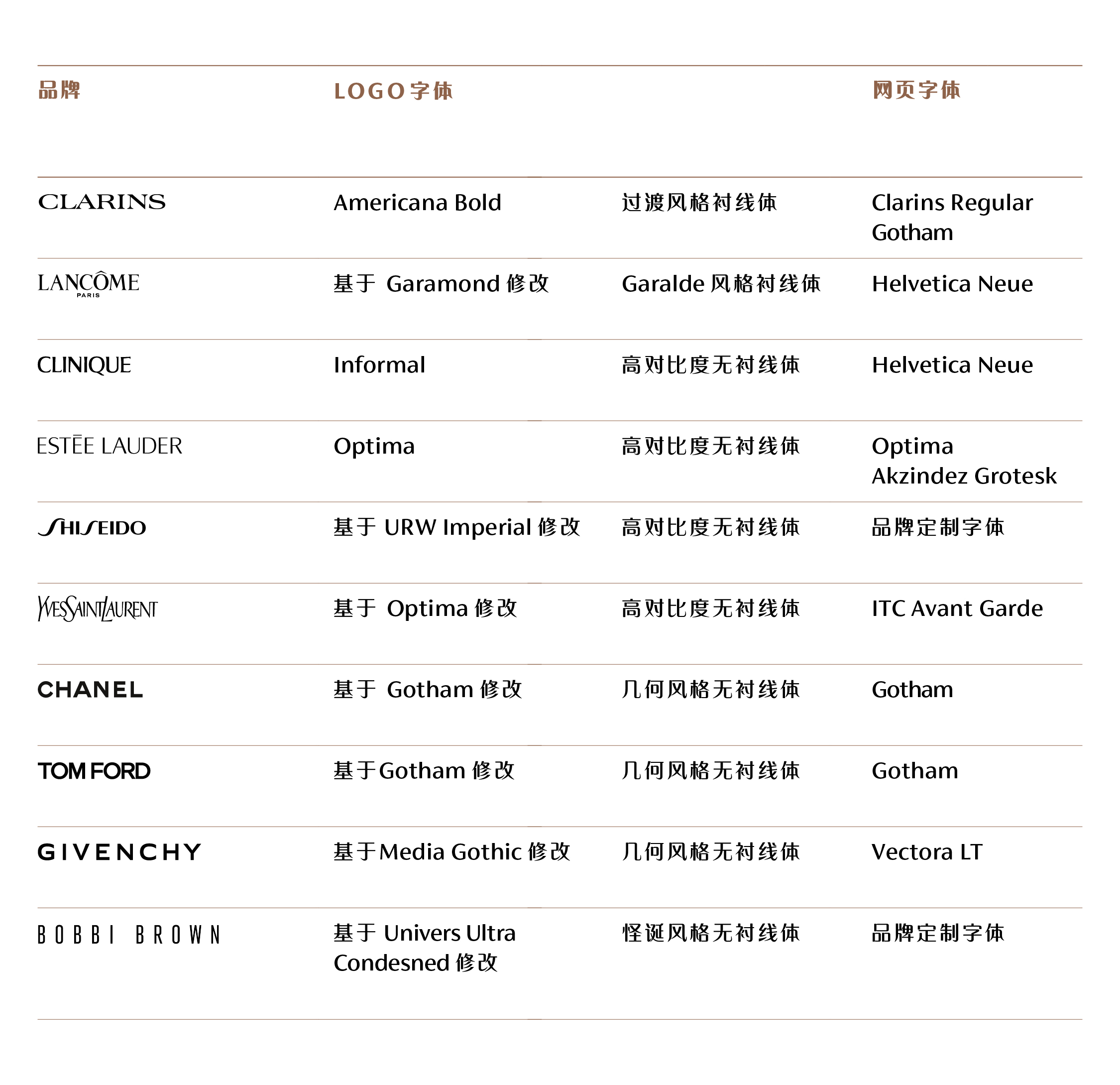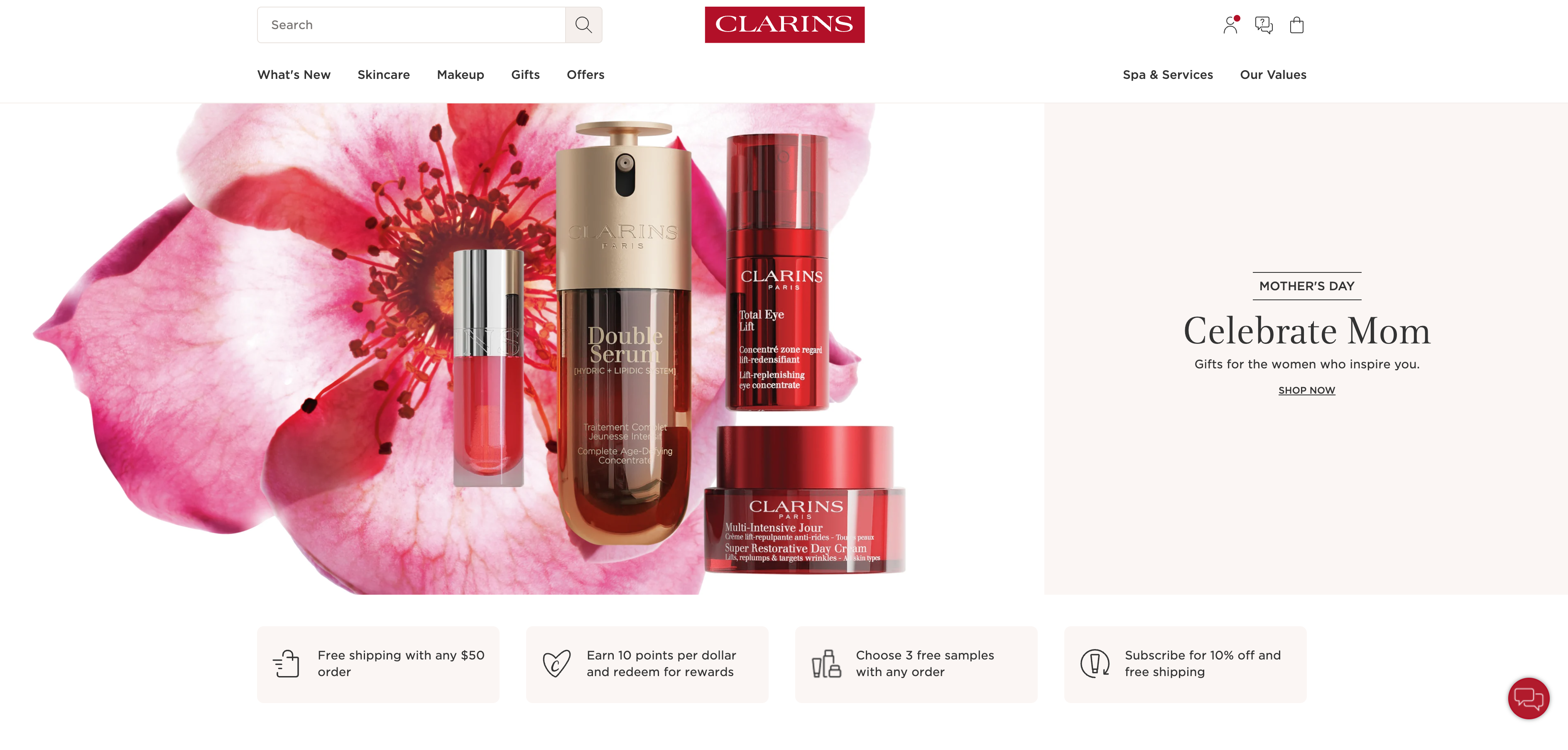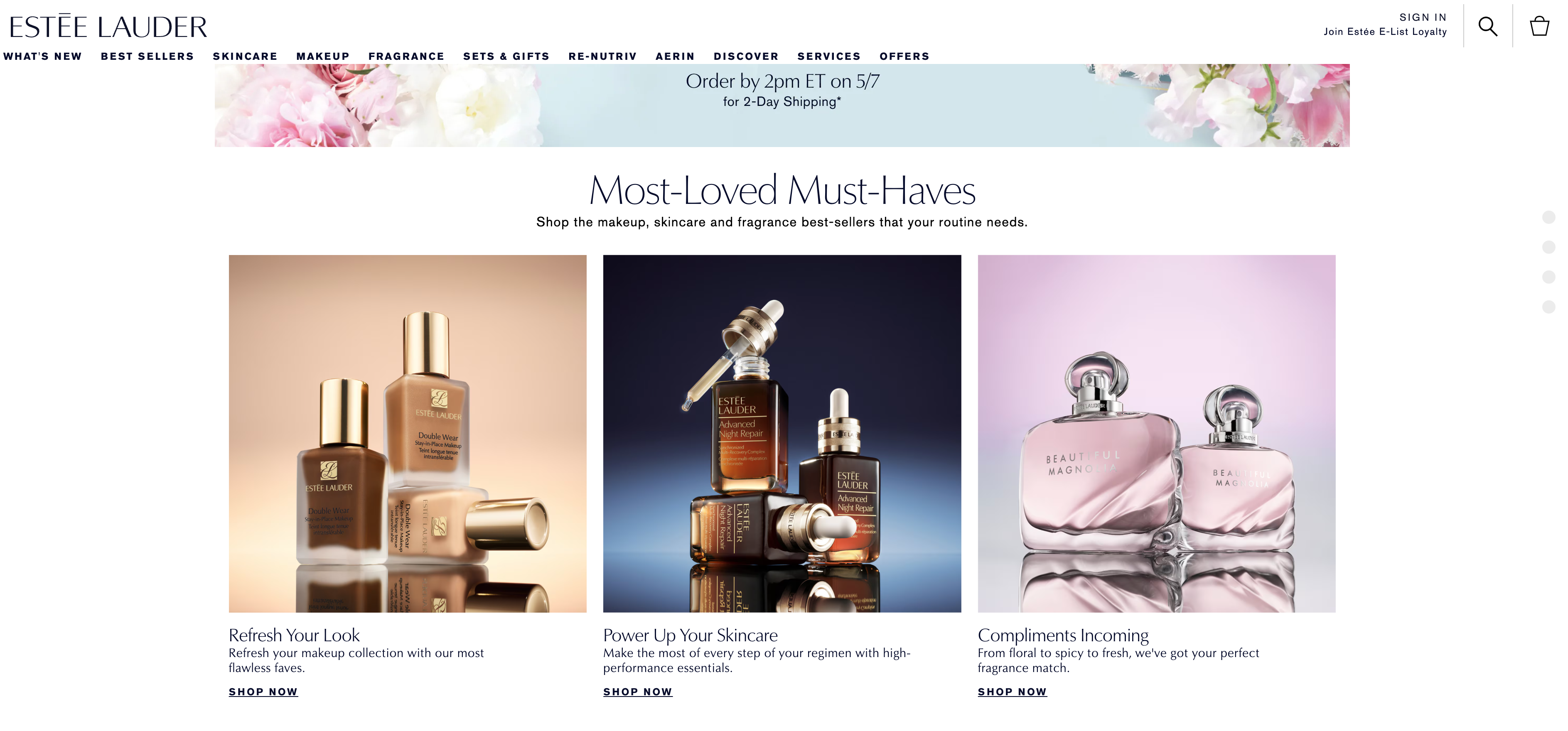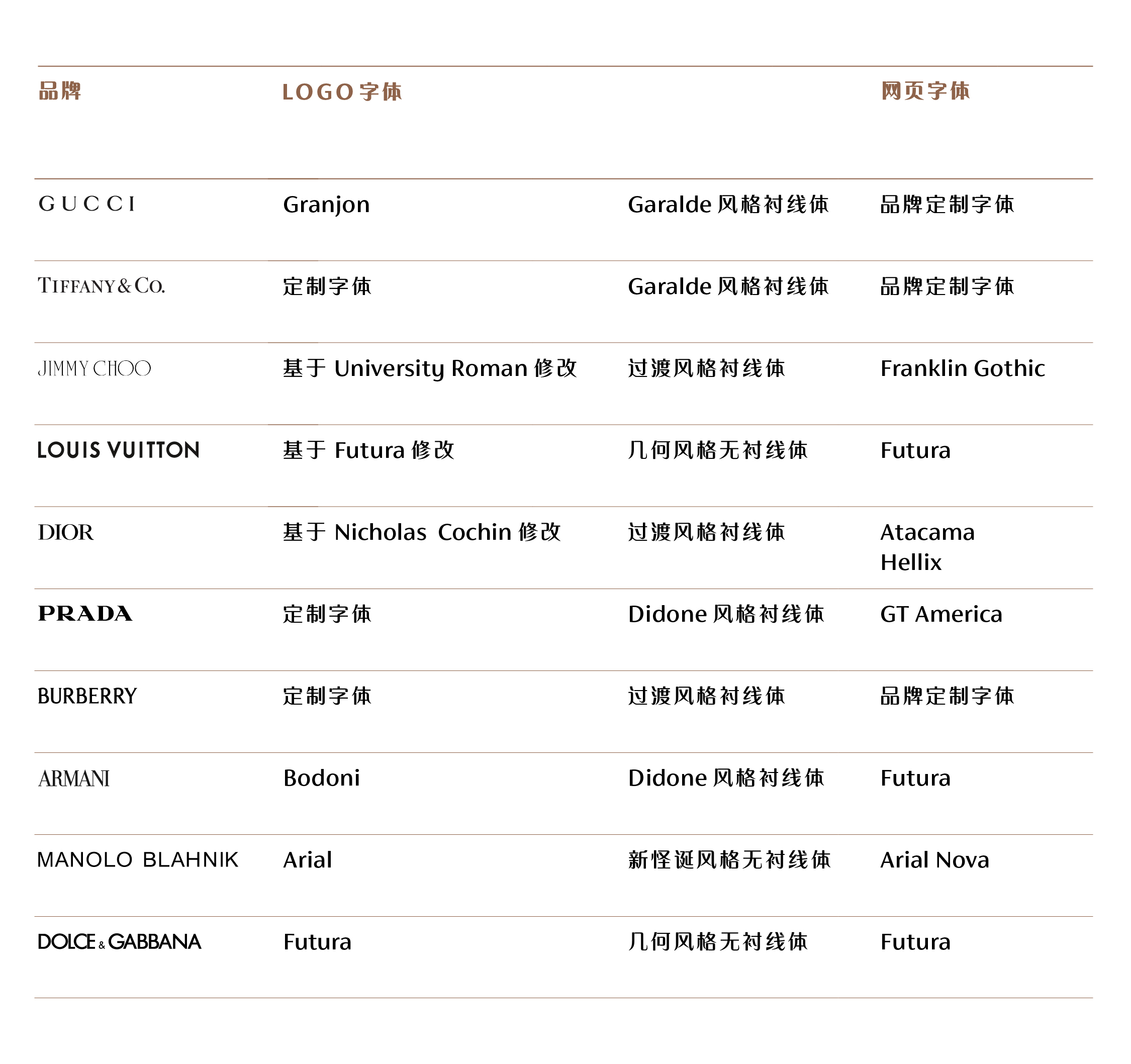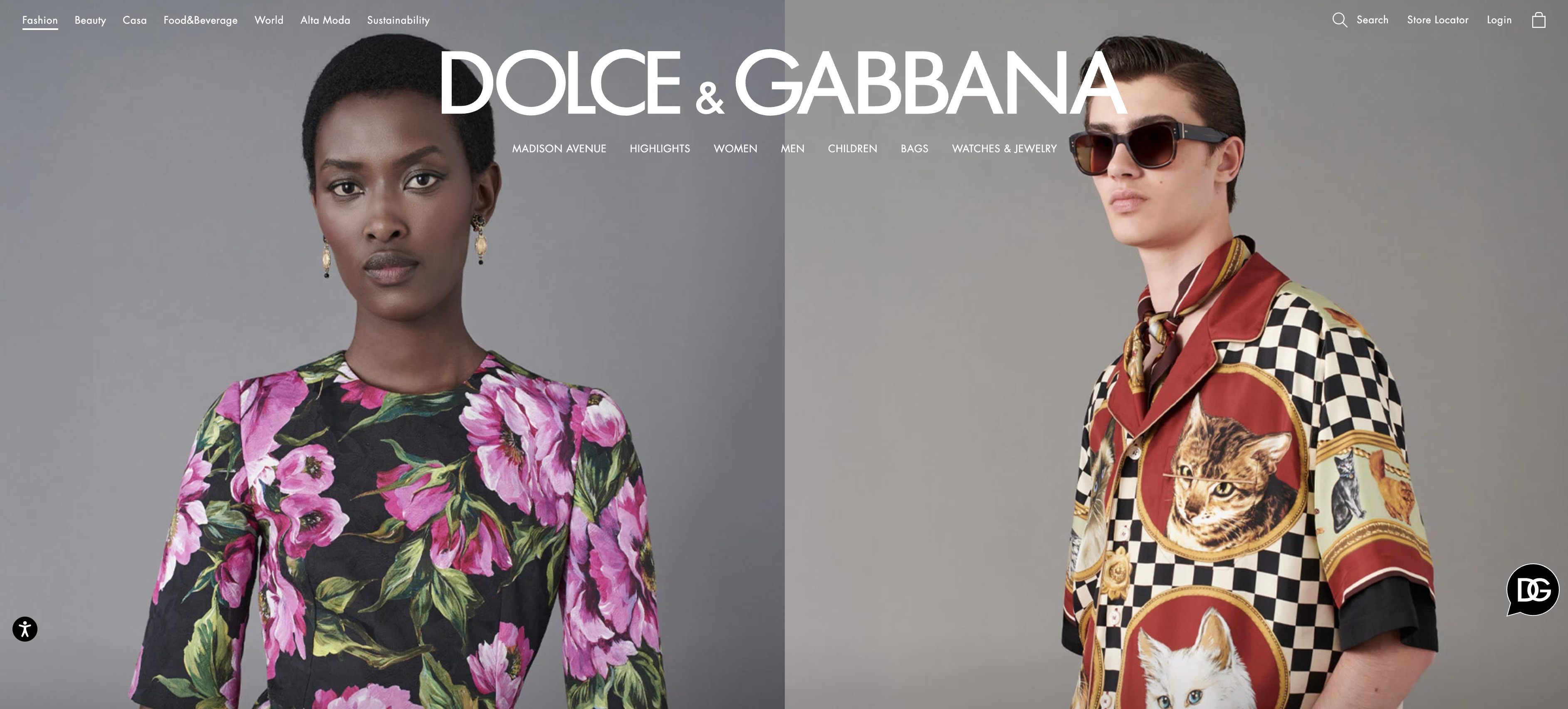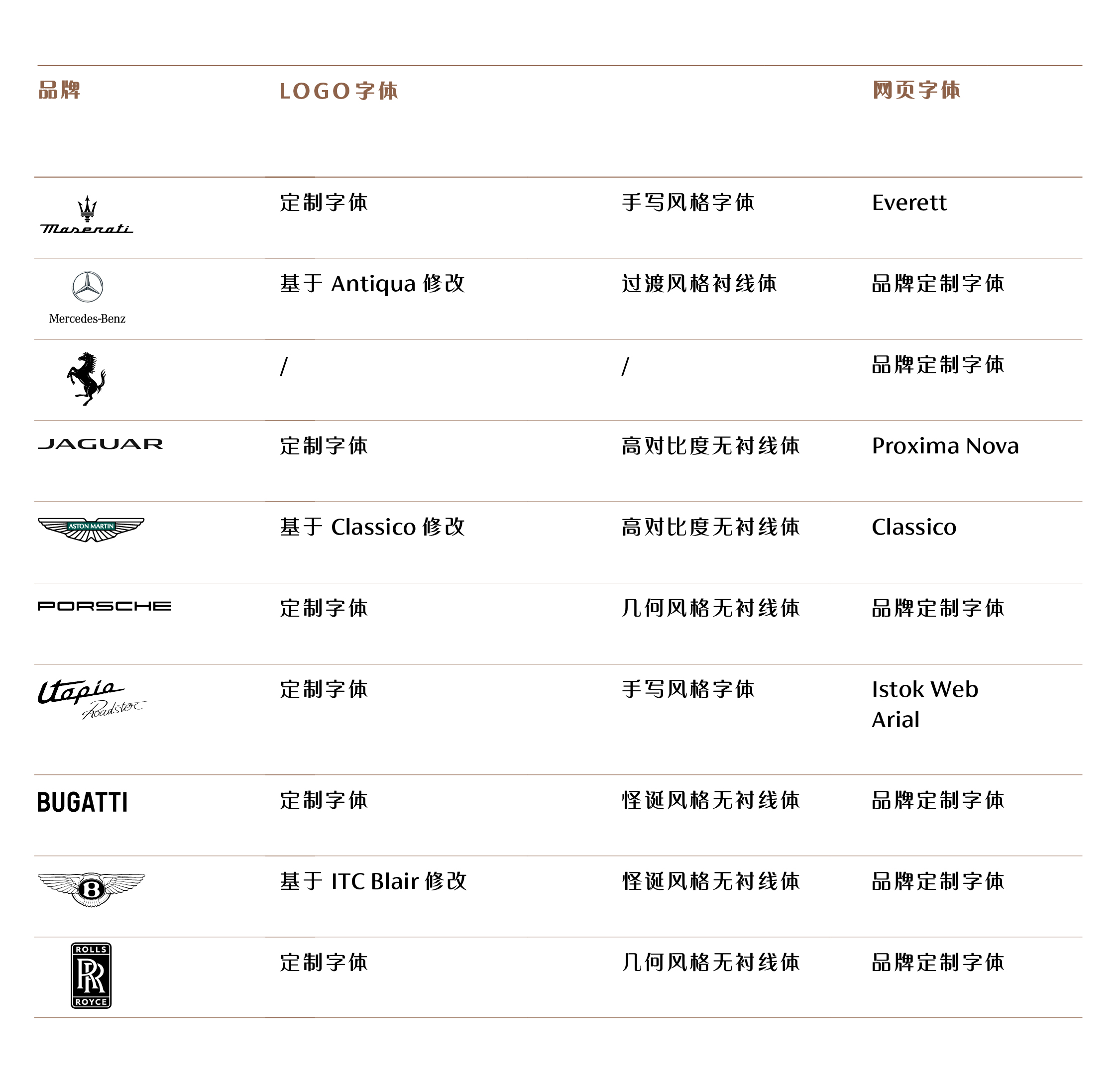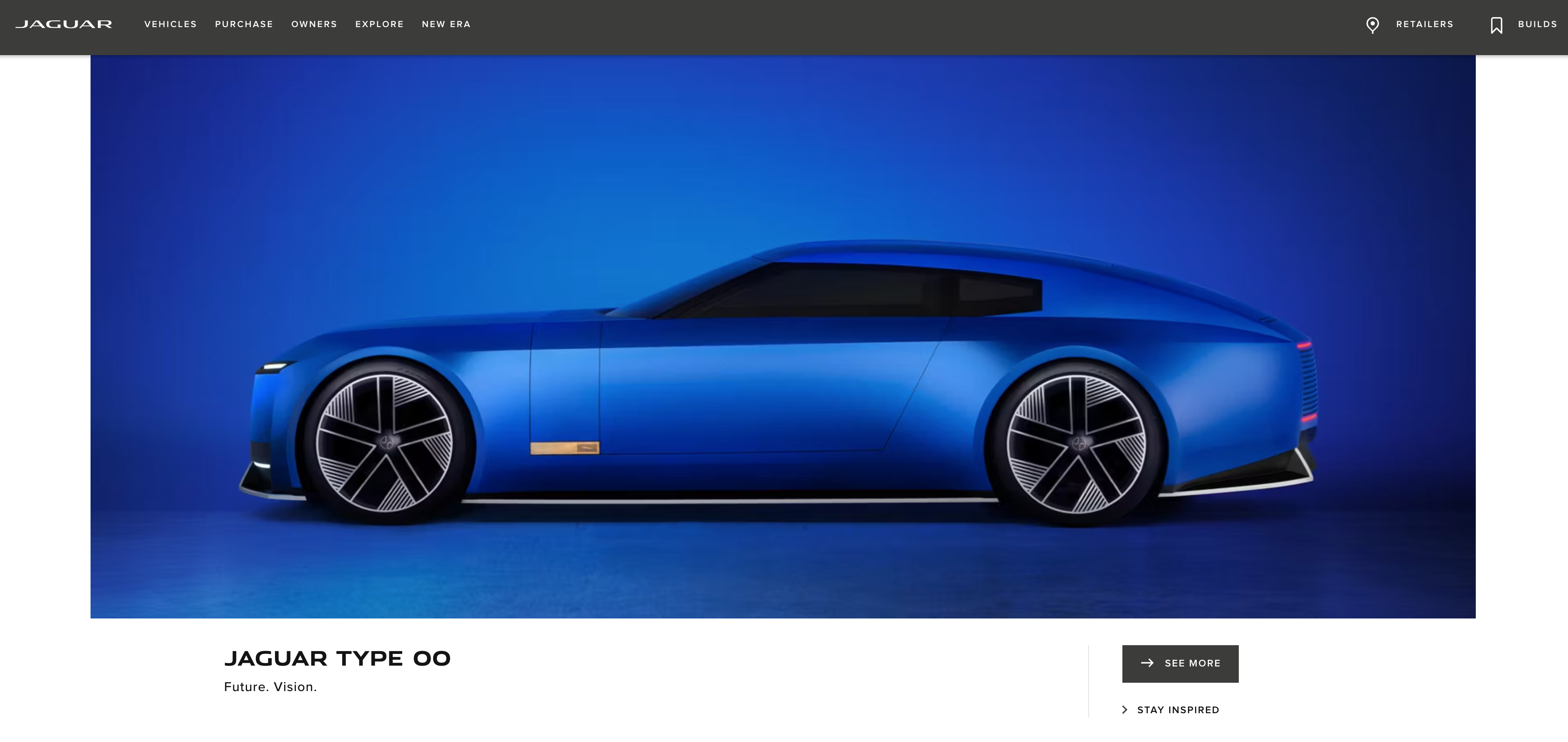
为什么一看就很贵?奢侈品牌在用这些字体策略……
导读:
提起「奢华感」,你会想到什么?是柔光下闪耀的 LOGO,还是印在包装上的那一抹优雅衬线?在数字化叙事的今天,奢侈品牌早已不再只靠金属印刷和高定剪裁取胜,屏幕上的每一个字体选择,都在无声中传递品牌的品位与态度。
本文聚焦美妆、时尚与汽车三大行业,剖析 30 个高奢品牌如何通过字体构建独特的视觉语言:全大写、衬线体、粗细对比明显的笔画……它们是否就意味着「奢华」?
如果你正在寻找打造高级感的灵感,或想让品牌在视觉上脱颖而出,这份关于字体的观察与分析,值得参考。
在数字时代,奢华早已不再遥不可及,你无需成为富豪,也能在社交媒体尽览顶级品牌的风采。正如广告公司 BETC 主席兼创始人 Rémi Babinet 所言:「奢侈的定义正在演变,它不再只是价格与稀有的代名词,更是一种能与时代对话的文化象征。」
在视觉传达上,字体正是连接传统与当下的关键,需要找到微妙的平衡:既承载底蕴,也要具备冲击力与时代感。
* 高对比度(High Contrast Sans Serif)指笔画粗细对比明显,本文其余部分亦同。
1.1 刚柔并济的字体美学
反直觉的是,美妆品牌并不都偏好纤细衬线体、柔和配色和华丽模特,反而常用黑白配色、大胆视觉和全大写字母,不仅 LOGO 和导航如此,甚至正文也不例外。
通过全大写字母和黑白极简配色,Tom Ford 在数字端传达出一股坚实自信的气场。
全大写虽在可读性上略有牺牲,但视觉风格更鲜明。Tom Ford 的官网完全不用小写字母,展现出强势、张扬又现代的气场。
有趣的是,几乎所有品牌 LOGO 都采用了全大写,其中超过一半使用笔画粗细对比明显的字体(如 Optima),40% 选择粗重无衬线体。网站主字体方面,七成偏好几何无衬线体,40% 使用高对比笔画设计,呈现出多样又鲜明的风格取向。
1.2 以行业通用字体构建「高级感」
香奈儿的 LOGO 使用了几何无衬线体 Gotham,凝练了品牌的优雅格调。网站也一以贯之,统一使用粗体全大写 Gotham,确保品牌调性。
这些品牌在字体选择上呈现出高度一致性,Gotham 和粗细对比明显的无衬线体 Optima 是最常见的选择。例如香奈儿标志性的全大写几何风格粗体,优雅而高贵,与品牌形象如出一辙。
娇韵诗选用了一款现代感的衬线体,风格接近 Baskerville,优雅得体,非常适合展现美妆产品的质感。
在强调差异化、却易被模仿的市场中,这种字体上的趋同颇为耐人寻味。对于初创品牌而言,通用字体也能帮助迅速复制出类似的高级感。
1.3 衬线体 VS 无衬线体
美妆行业的字体大致分为两类:一类借助衬线和粗细明显的笔画营造传承感,另一类则偏好几何或更张扬的字体,追求现代与个性。后者若搭配得当,同样能展现奢华气质,但更需在视觉上与平价品牌拉开差距。
雅诗兰黛网站融合轻盈纤细的 Optima 字体、大篇幅精致图像,以及品牌标志性的深蓝色,整体氛围正式而不失优雅。
尽管衬线体常被视为更具高端气质,但实际使用并不广泛。娇韵诗与兰蔻凭借现代衬线体打造出独特的经典感,而雅诗兰黛采用的 Optima,也展现出优雅与辨识度。
在竞争激烈的市场中,脱颖而出并非易事。相比其他行业,美妆品牌更倾向于选择不那么普遍泛用的字体,以增强辨识度和品牌印象,区别于竞争对手。
2.1 极简之中见锋芒
多数时尚品牌以大胆摄影搭配简约字体,风格与美妆行业相近:留白充足、色彩强烈,偏好几何风格或笔画粗细明显的字体。
杜嘉班纳的 LOGO 及网页主字体都选用了 Futura,以几何理性的结构传达出现代感与坚定气质。
在网页主要字体的选择上,几何无衬线体尤为流行,占我们调研品牌的 80%,最常见的是 Futura(美妆品牌们则更偏好 Gotham),也有部分品牌在近几年启用了自己的定制字体。
2.2 衬线体与全大写
70% 的品牌 LOGO 采用了衬线体,传递出经典感,但纤细笔画在屏幕、尤其小尺寸下易失真。这些字体多为印刷时代设计,难以适应数字环境,因此一些品牌即便视觉设计出众,网页内容仍使用系统默认字体。
迪奥官网以衬线体为主,无衬线体为辅且全大写排版,构建起优雅纤细的视觉观感。
和美妆、汽车行业类似,全大写也非常常见。调研的十个品牌中,有九个在导航菜单和 LOGO 中采用了全大写,唯一例外是 Dior。
2.3 在移动端占据用户心智
品牌识别至关重要,而字体正是其中最容易被忽视、却极具辨识度的要素之一。虽然并非每个品牌都深入了解字体细节,但在构建品牌价值、传递调性时,它所起的作用不容小觑。
尤其在移动端这个展示空间有限、用户注意力高度分散的主战场中,一款精心挑选且与品牌高度契合的字体,往往能在第一时间传达出品牌的格调与专业性,成为区别于其他品牌的关键视觉符号。
3.1 力量背后的优雅设计
汽车行业仍被普遍视为男性主导的领域,因此,观察它是否与传统上面向女性的美妆和时尚行业在字体使用上存在相似之处,颇具趣味。
在字体选择上,车企需权衡诸多要素:如何在传达力量、速度与精准的同时,也体现奢华感?
3.2 LOGO 的多样性
在 LOGO 字体上,汽车品牌呈现出丰富多样的风格,从旧式、板状衬线体,到几何、怪诞、人文主义无衬线体皆有覆盖。
奢华感的表达也分为两类路径:一类偏好坚固、现代的模块化设计,另一类则通过高对比衬线体强调优雅与工艺。
3.3 定制加持,打造专属品牌语汇
捷豹与 Fontsmith 合作定制的字体呼应了 LOGO 的字形比例,保持品牌风格一致性。此外还为标题文字应用了 Proxima Nova 这款经典无衬线体。
豪华汽车品牌普遍偏好视觉感强烈的主字体,常见类型包括人文主义、怪诞或几何风格的无衬线体,如 Proxima Nova、Gill Sans 等。在我们调研的十个品牌中,有一半使用了定制或重命名字体,展现了它们对独特性与品牌专属感的重视。
阿斯顿·马丁官网用 URW Classico 营造出统一和谐的美学效果。
相较于美妆和时尚行业,车企更注重字体在品牌识别中的角色,并借助品牌深厚的历史赋予其更多意义。例如阿斯顿·马丁便采用了 URW Classico(一种 Optima 变体),以优雅精致呼应其顶尖工艺。整体来看,汽车品牌倾向于选择成熟、有力的字体,辅以定制设计,强化高端定位。
洞察与总结
当我们总览这横跨三大行业的 30 个高奢品牌用字,不难得出以下观察:
● 在 LOGO 设计中,不同行业对无衬线字体的使用比例有着明显区别。
美妆与汽车品牌更偏好通过无衬线体传达现代感、简洁性和力量感,而时尚品牌则更倾向于借助衬线体来营造优雅、经典、富有传统底蕴的品牌印象。
● 无衬线体在网页主字体中的使用比例非常高,显示出其在数字端的主导地位。
89% 的豪华汽车品牌、81% 的美妆品牌,以及 71% 的时尚品牌在网页中使用无衬线体作为主要字体。无衬线体以简洁、现代、适应性强的特性,契合了当前数字化设计趋势。
● 在奢侈品牌的线上呈现中,全大写排版依然是一种高度普遍的视觉策略。
但值得注意的是,仅有 3% 的品牌在正文文本中使用全大写,说明品牌在强调视觉识别的同时,仍会在可读性和用户体验上做出权衡。这种「只在关键位置全大写」的做法,体现出品牌在现代数字环境中对形式与功能的精细拿捏。
在数字时代,字体不只是视觉元素,更是奢侈品牌识别与格调的核心:从 LOGO 到网页主字体,从是否全大写到是否定制字体,各大品牌通过字体传达各自的个性与定位。
尽管趋势趋同,品牌仍需在相似的设计语言中打造差异化。字体,正是帮助品牌在饱和市场中脱颖而出的关键资产之一。